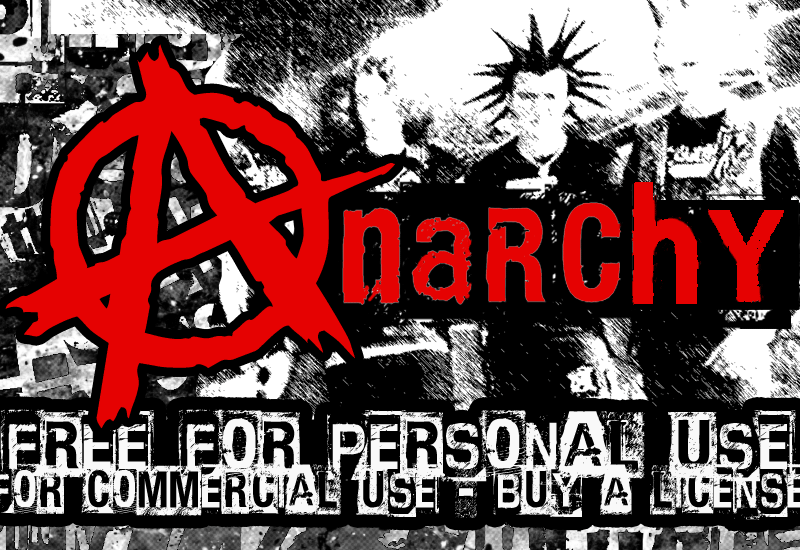
A fonte ‘CF Anarchy’ é uma escolha perfeita para criar designs atrevidos e vibrantes no design visual. Criada por CloutierFontes em 2013, a fonte ‘Anarchy’ combina elementos de tipografia brutalista com nuances mais suaves, resultando num estilo que transmite energia e originalidade sem perder o controle. Esta fonte é ideal para designers que buscam uma opção expressiva para criar letras chamativas e efêmeras em projetos de design web ou criações gráficas digitais. Para uso pessoal, a fonte está gratuita. No entanto, para usar a fonte em propósitos comerciais, como desenvolvimento de software ou criação de produtos com fins lucrativos, é necessário adquirir uma licença. Este design único e impactante torna a ‘CF Anarchy’ uma opção ideal para quem deseja imprimir um toque inconfundível de revolução na sua identidade visual.